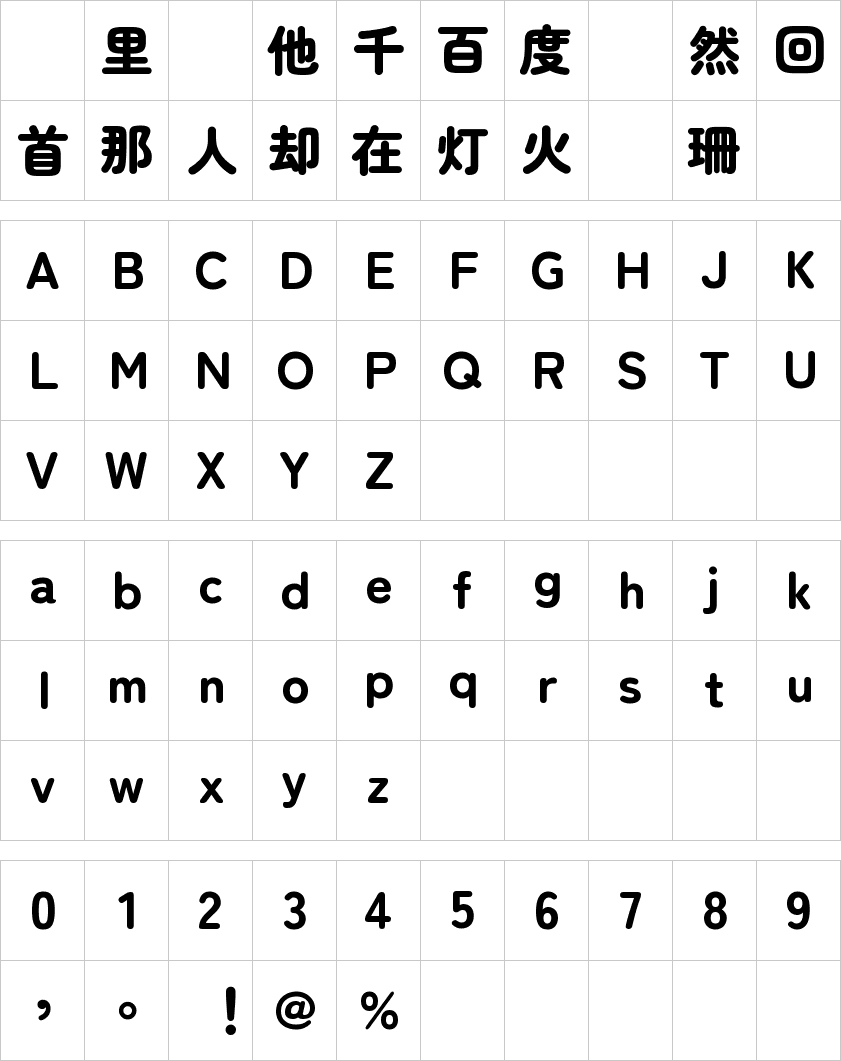
Natsuzemi Maru Gothic
○特徴 夏蝉丸ゴシックは、レトロな雰囲気が特徴の丸ゴシック体です。 Zen角ゴシックAntiqueを角丸加工した仮名とZen丸ゴシックを合成しました。 ○ライセンス SILオープンフォントライセンスの下で配布され、商用利用もできます。 当フォントはZen角ゴシック、Zen丸ゴシックの派生フォントです。 製作者様方に深くお礼申し上げます。